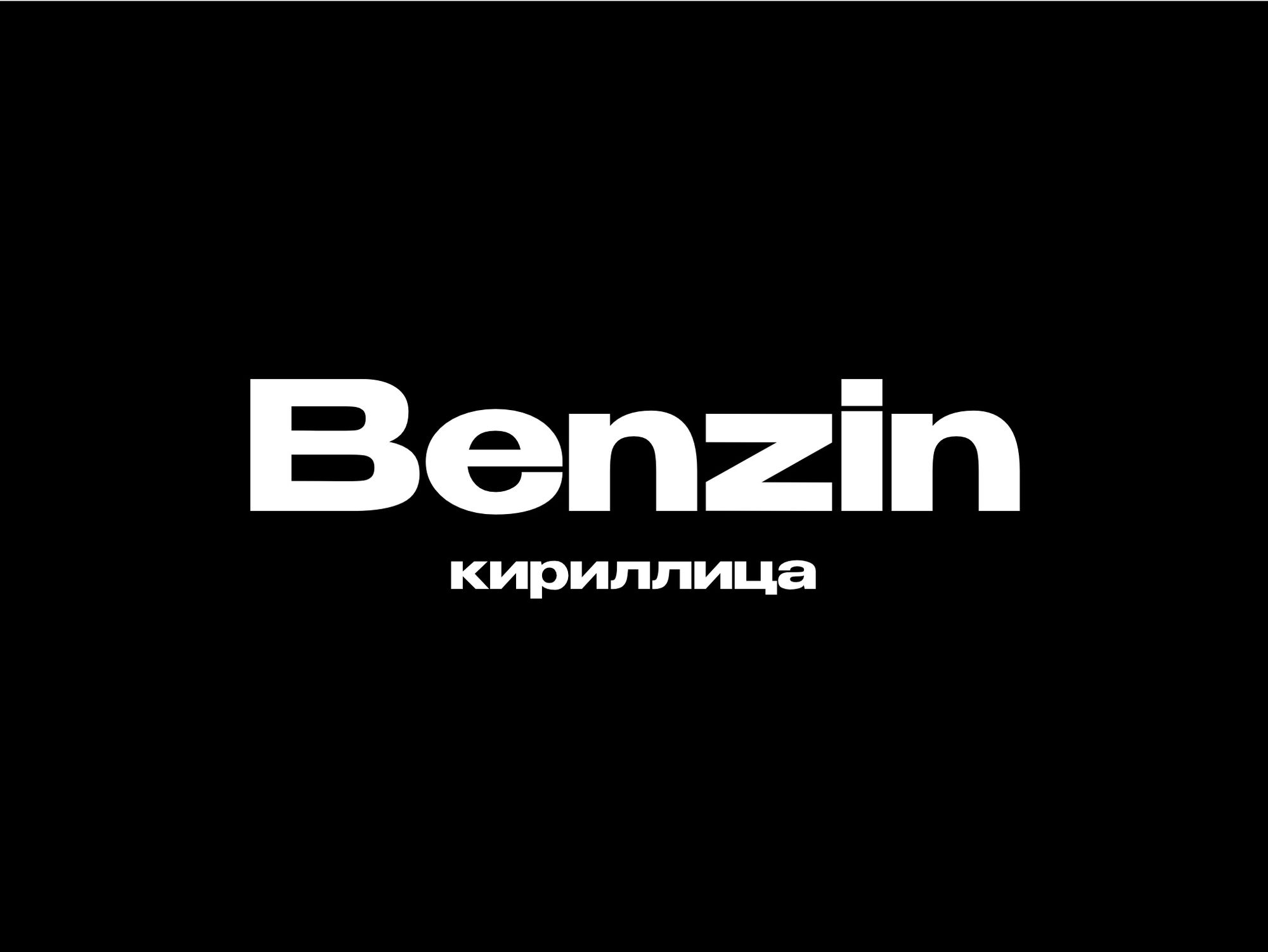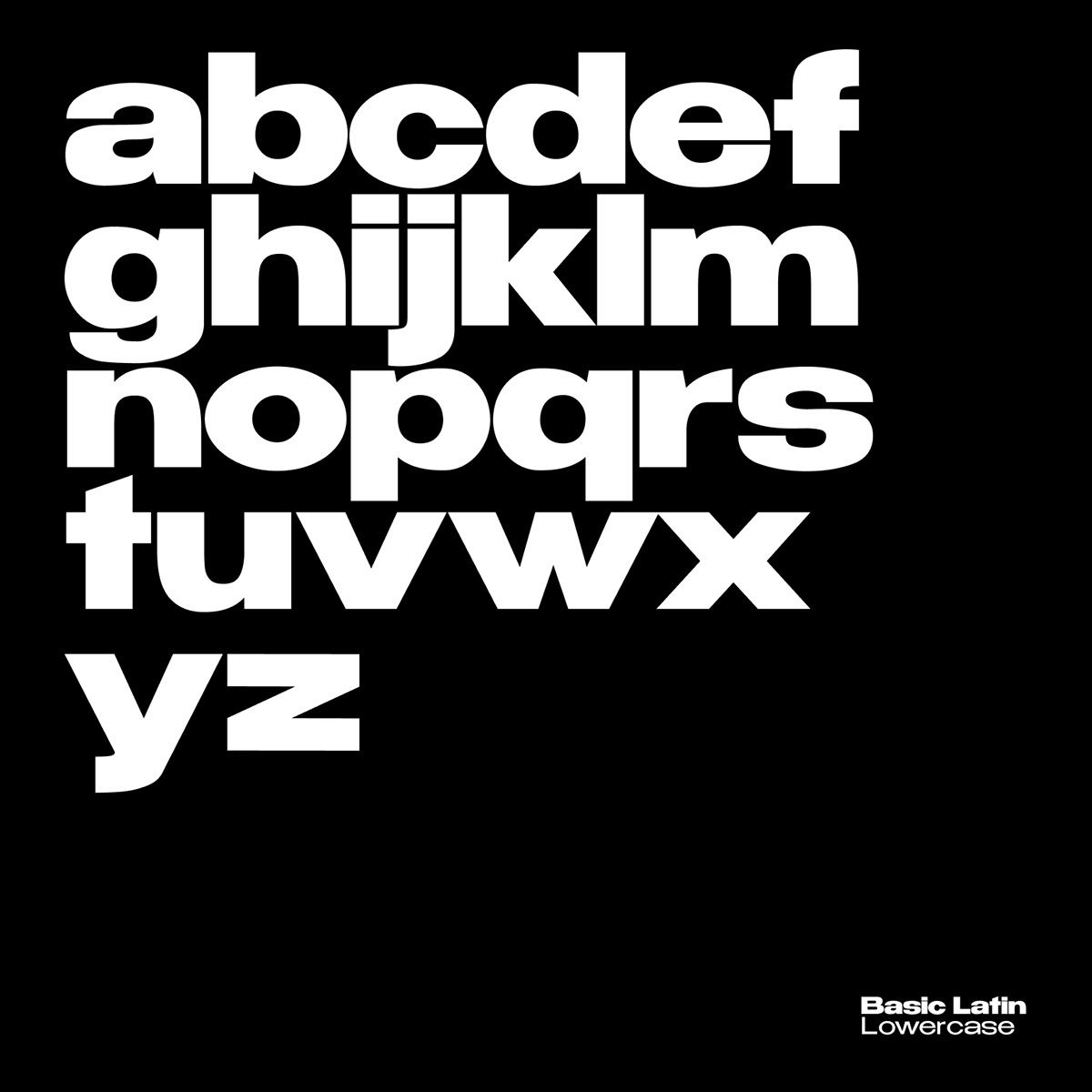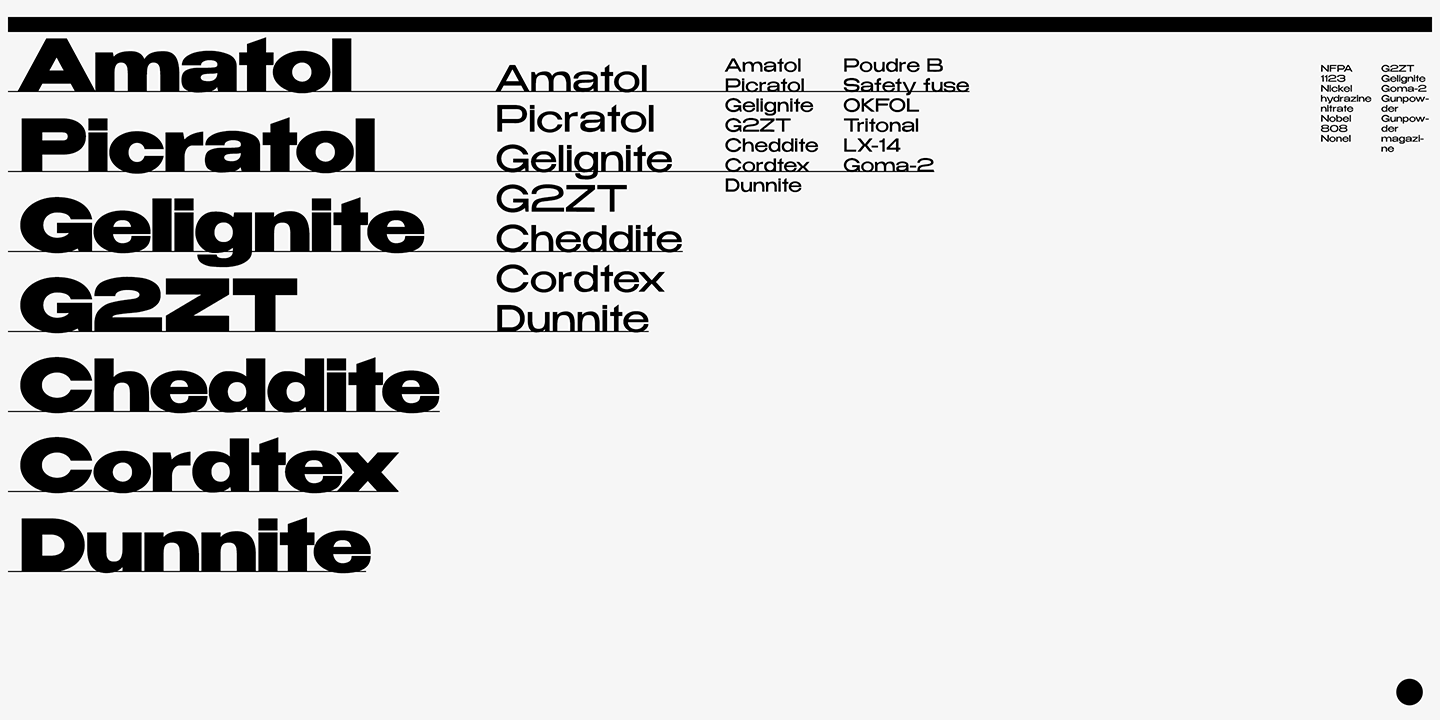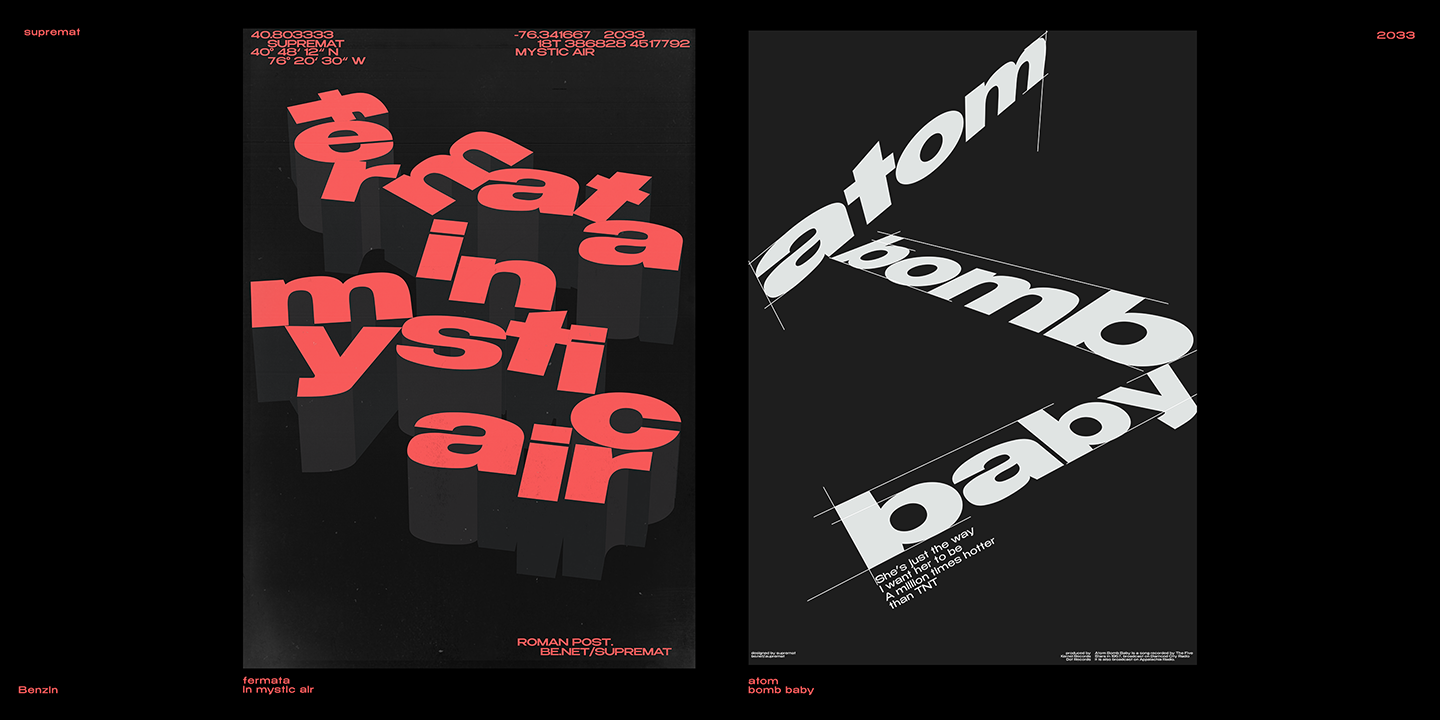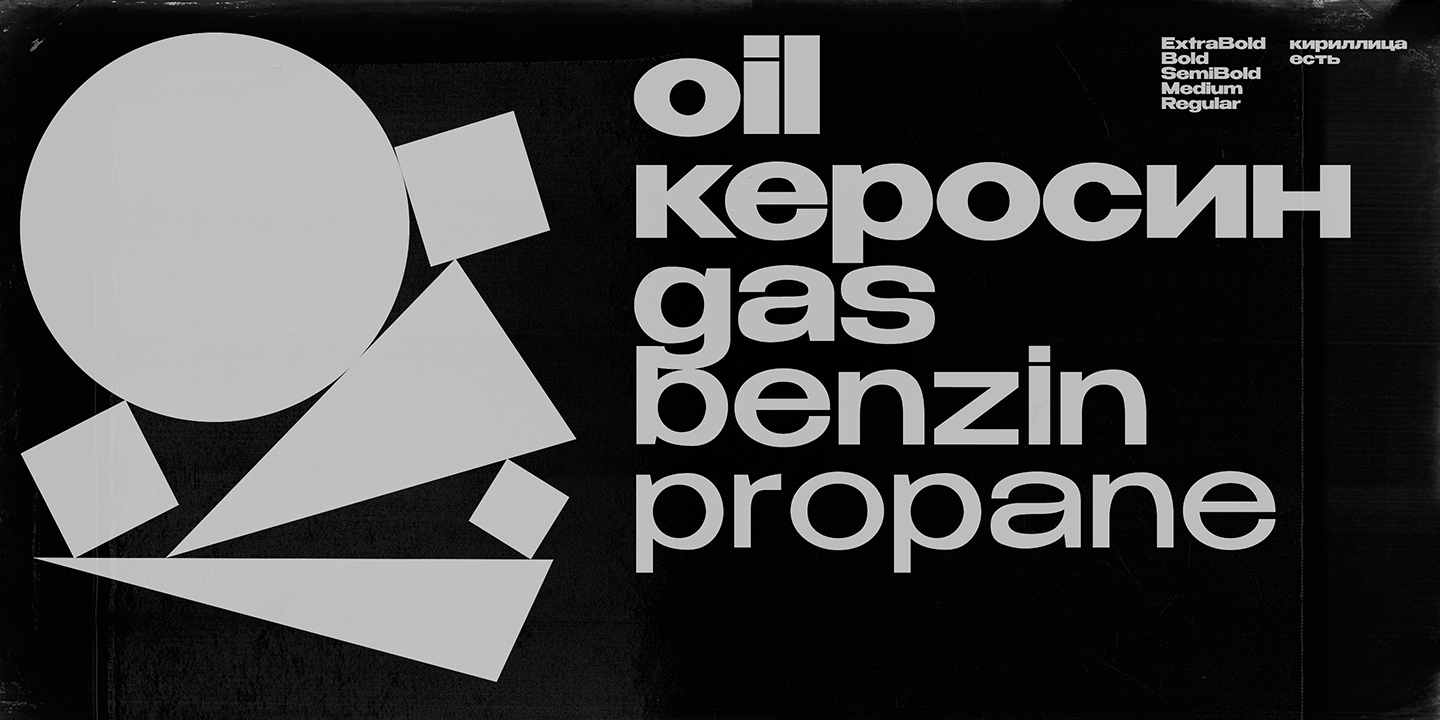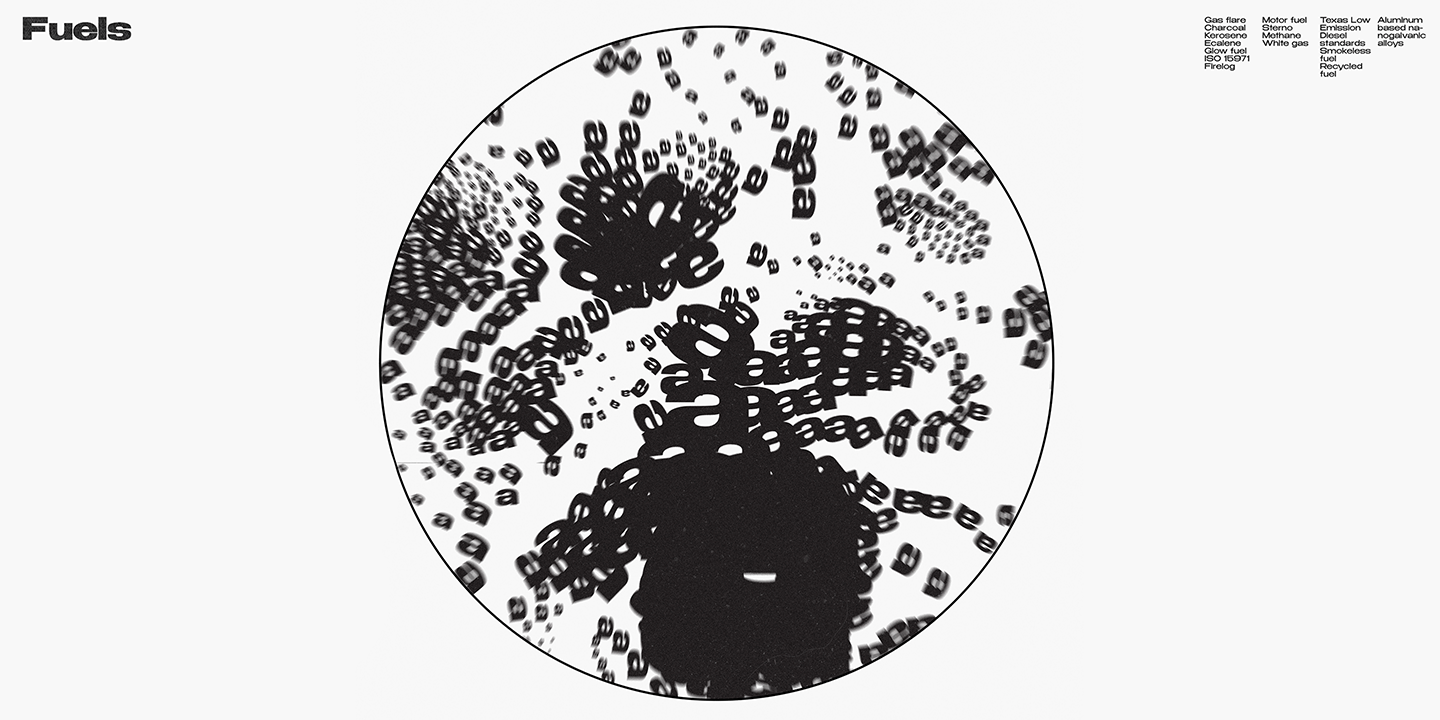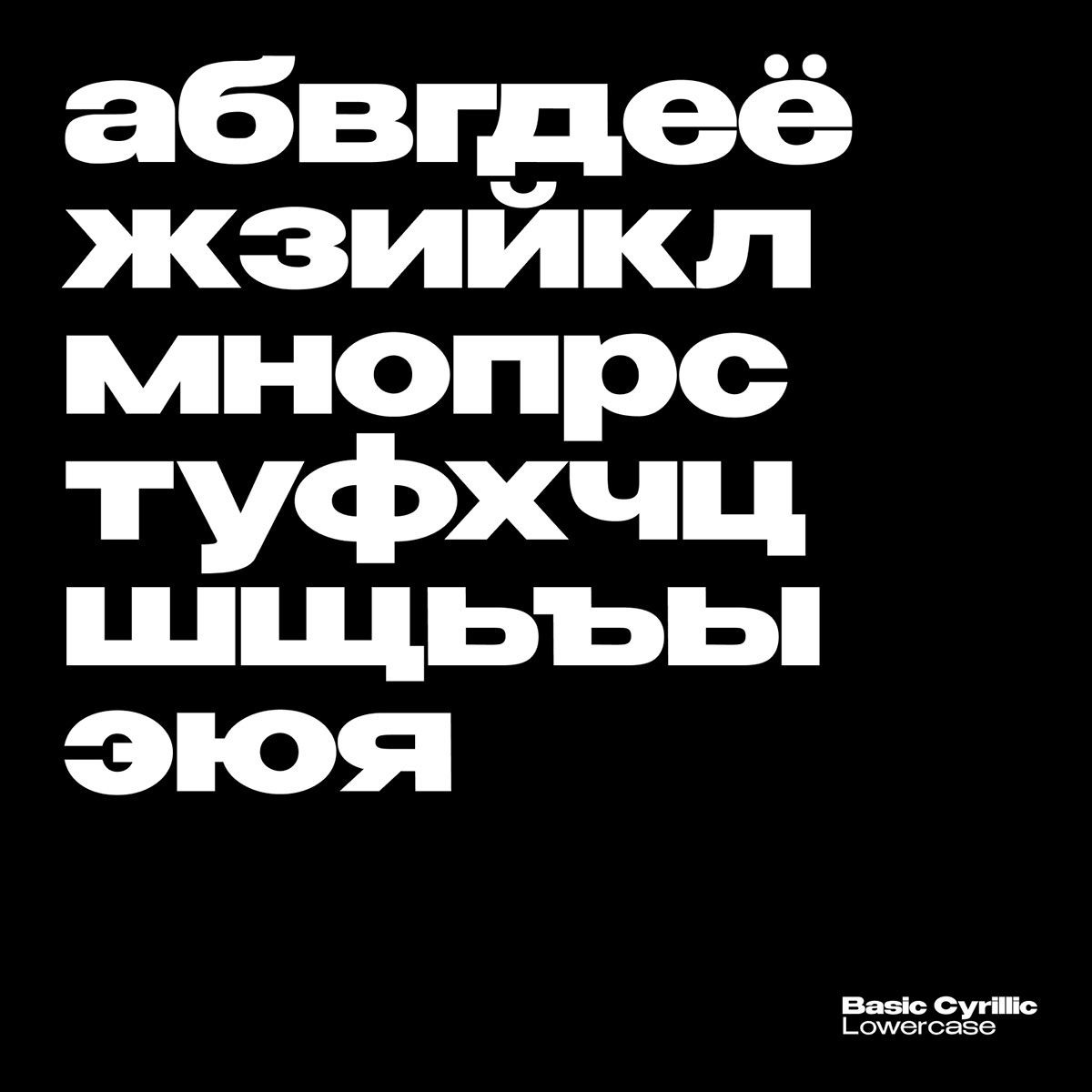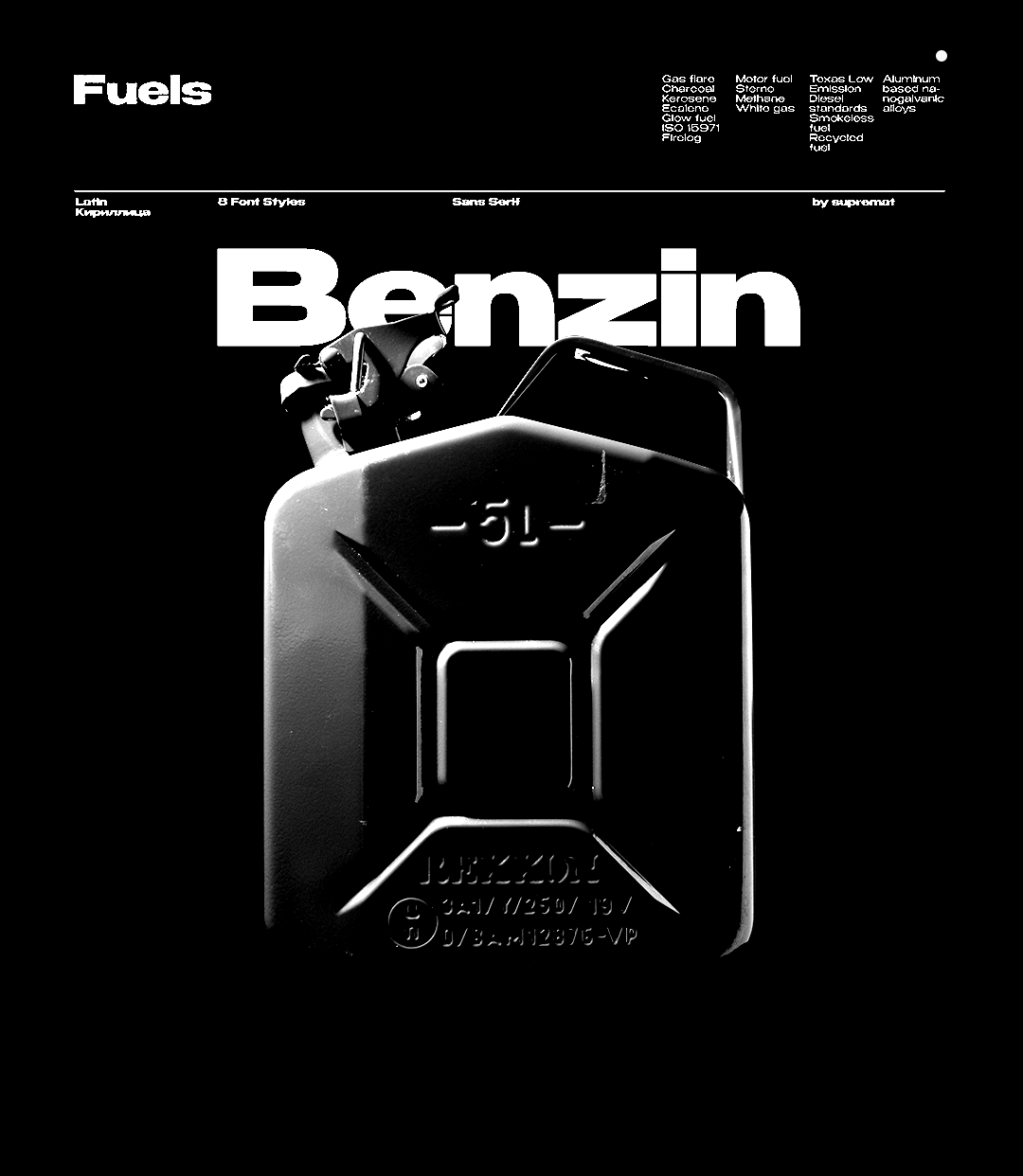
Benzin шрифт
Benzin — трендовый кириллический шрифт 2020 года. Разработанный российским дизайнером Романом Постовым.
Типографика всегда вдохновляла меня. Я часто фотографирую плакаты на улицах, отдельные буквы или слова на стенах, этикетки продуктов или логотипы. Меня очень впечатлила типография периода Баухауса и периода швейцарской типографики. Это вдохновение сильно повлияет на работу плакатов в будущем. Шрифты повсюду вокруг вас, и теперь мне нравится создавать свои собственные шрифты. Роман Постовой.